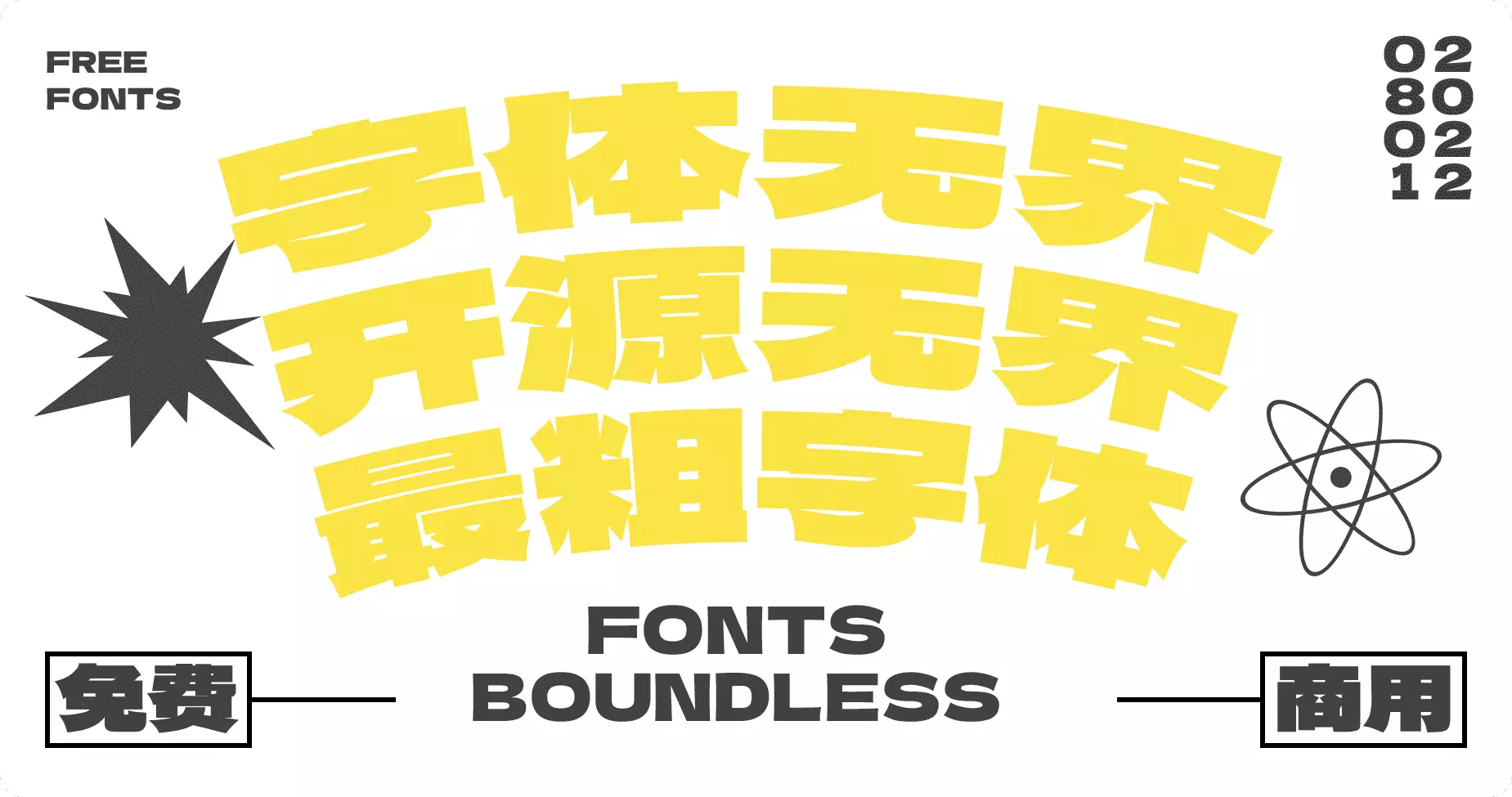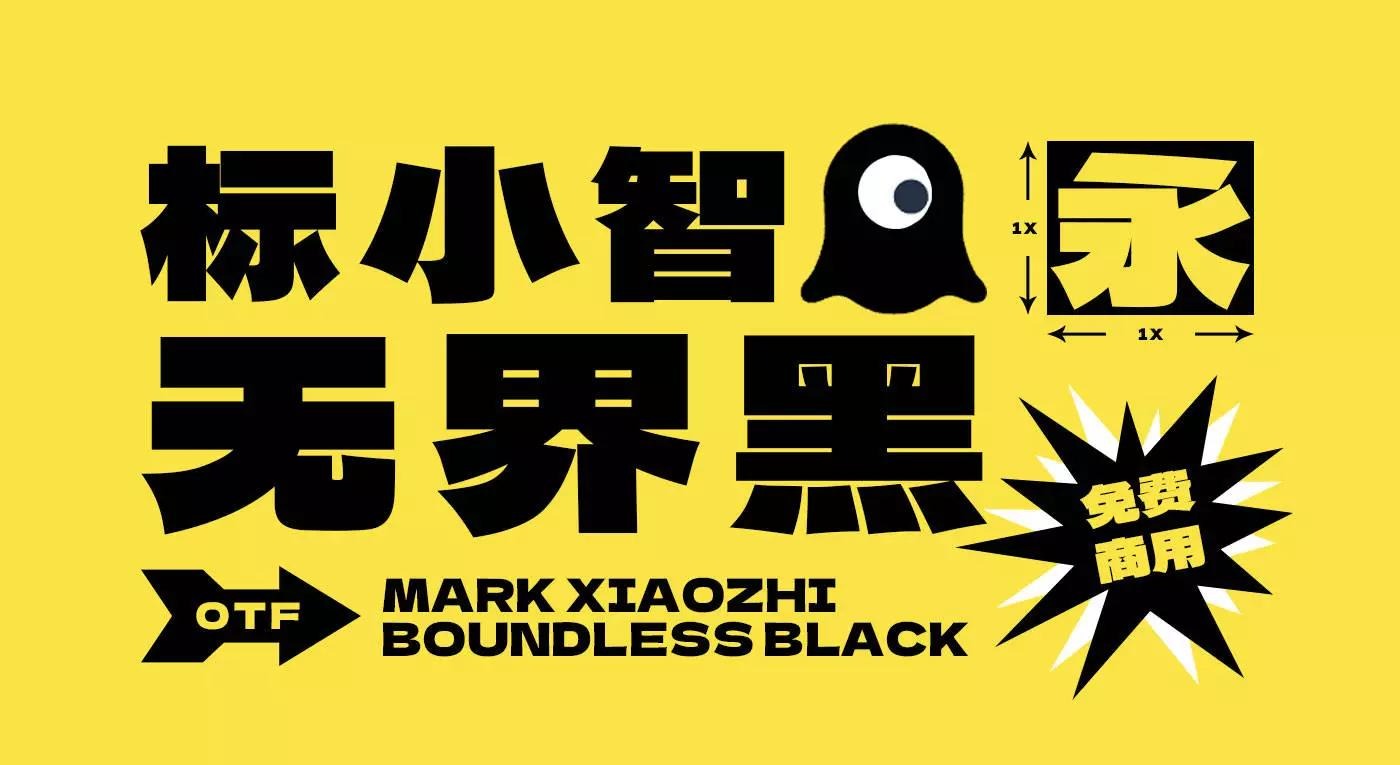
标小智无界黑 (LogoSC Unbounded Sans)是由在线 LOGO 设计平台标小智联合猫啃网推出的一款免费可商用的超粗黑体中文字体。
标小智无界黑基于日本开源字体德拉黑体 (Dela Gothic One) 改造,按照 GB2312-80 字体标准,将其全面修正为中国国标简体字形,彻底解决了日文字体在中文场景下的字形错误、阅读违等问题。
字体覆盖常用汉字、拉丁字母、数字与符号,采用扁平化设计。字形方正,笔画粗厚,整体风格硬朗、稳定、醒目,非常适合用于品牌 LOGO、海报主标题、包装设计、短视频字幕、户外广告等场景。